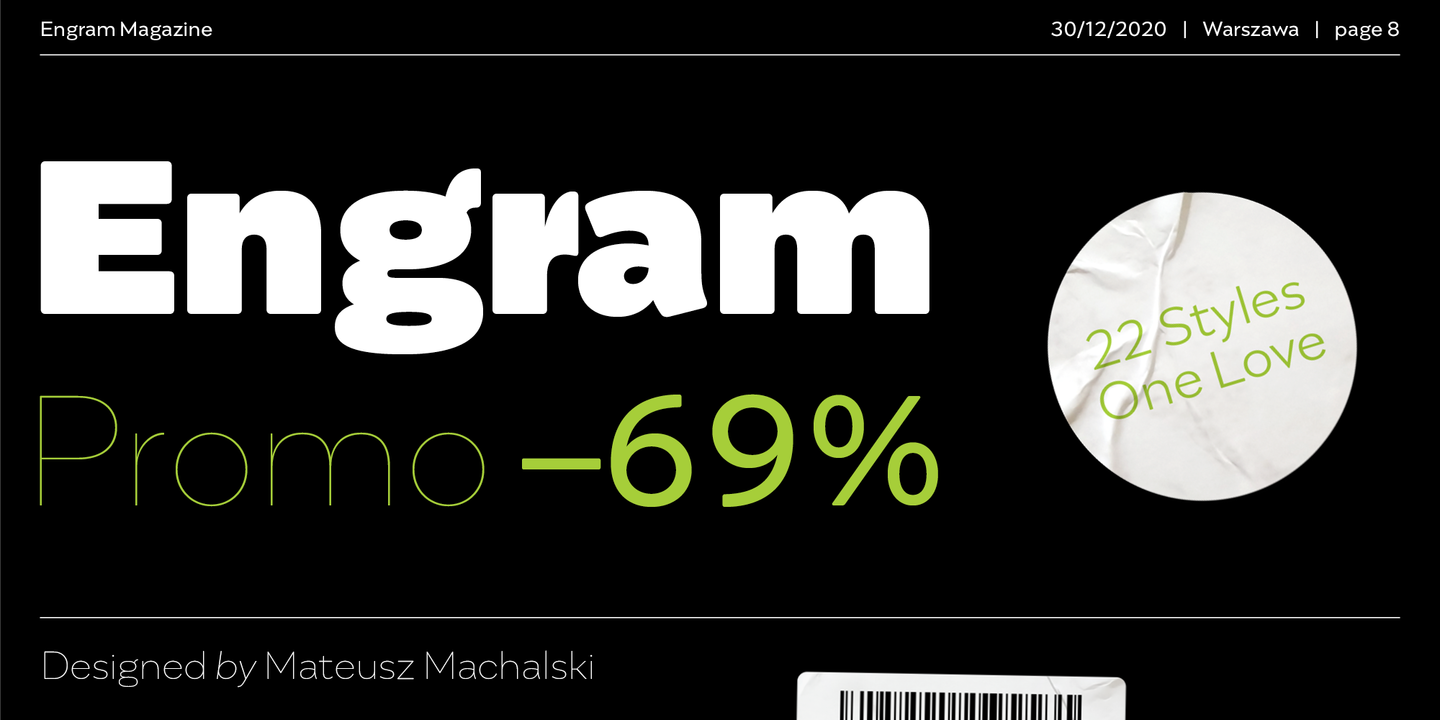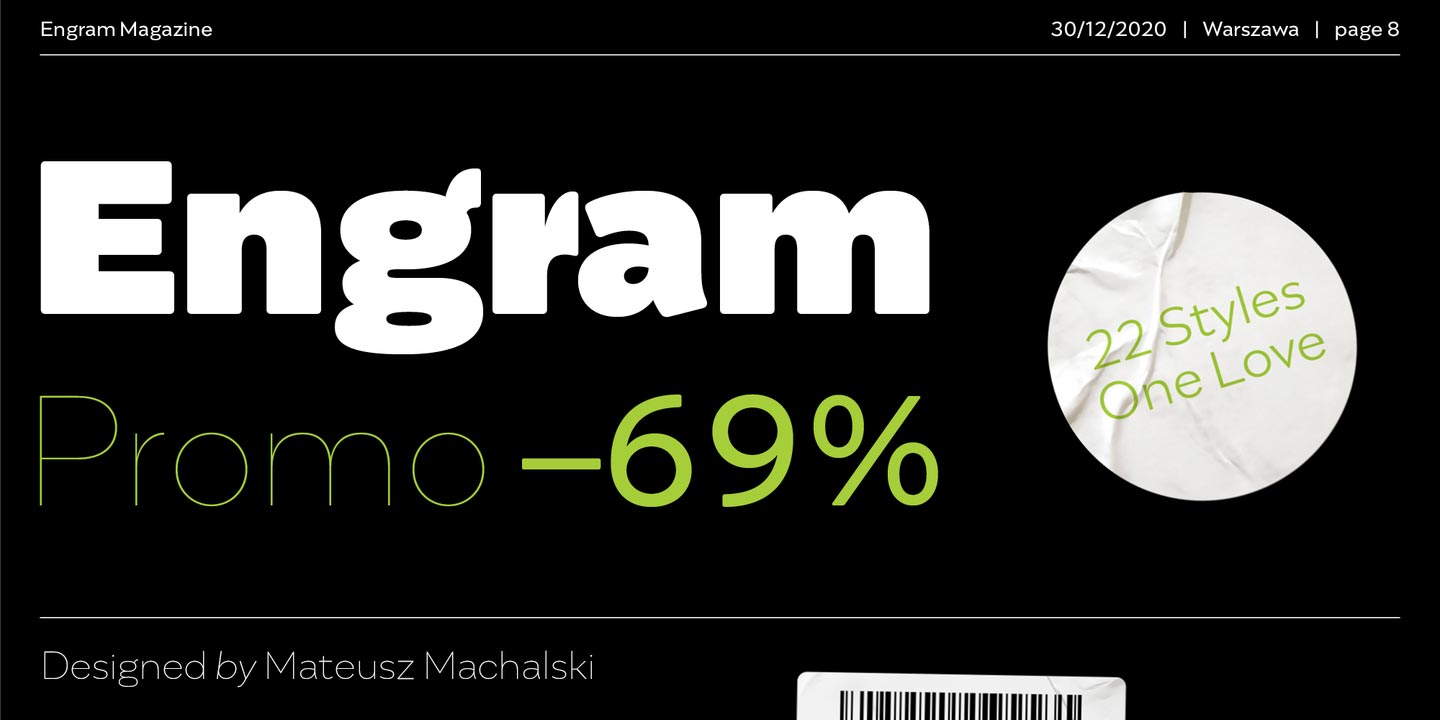
Engram (2015-2020) که توسط Mateusz Machalski طراحی شده است یک خانواده هندسی کلاسیک است. این نوع متن با جزئیات زیادی مشخص می شود که به آن شخصیت دوستانه ای می بخشد. ارتفاع x مقیاس پذیر ، گوشه های گرد ، Engram را برای بسیاری از اهداف انتخاب خوبی می کند. تمام خانواده ها از 22 خط با حروف کج از خط مو تا سیاه تشکیل شده اند.
Engram (2015-2020) designed by Mateusz Machalski is a classical sans geometric family. This typeface is characterised by a lot of details, which gives it a friendly character. Scalable x height, rounded corners makes Engram good choice for many purposes. All family consist 22 styles with italics from Hairline to Black.